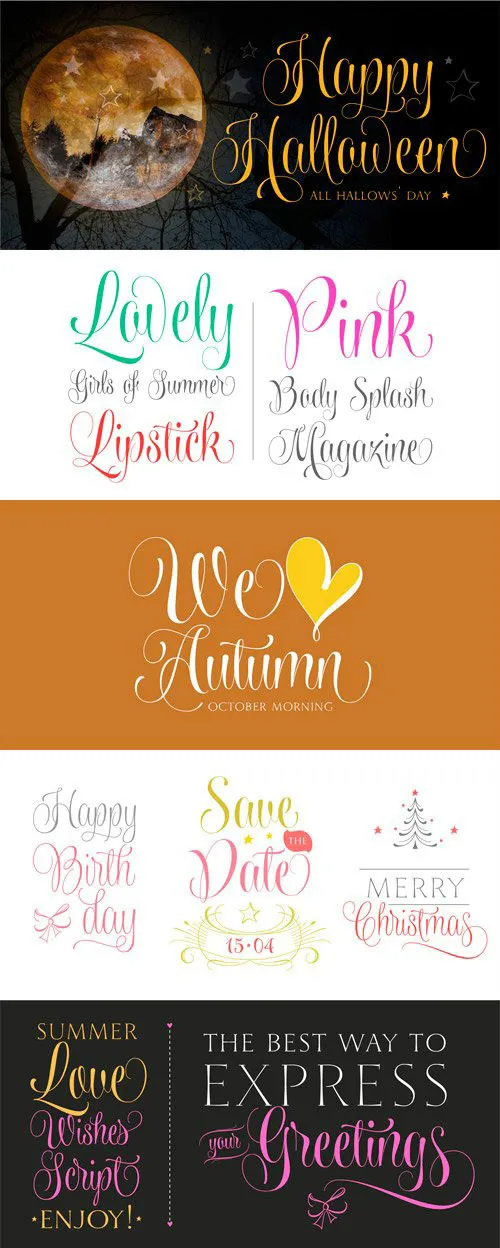
Wishes Script Font – Download Grátis
A Wishes Script Font é uma elegante escolha para designers que buscam adicionar um toque romântico a seus trabalhos digitais. Com traços fluidos e curvados, essa fonte script se destaca com um charme único que combina elementos femininos suaves com sutileza em cada letra. Perfeita tanto para gráficos de casamento quanto para criações de arte, ela representa uma maneira criativa e encantadora de incorporar detalhes personalizados em projetos. Inspirada pela designer Hamilton, essa fonte traz uma atmosfera de serenidade ao trabalho onde você a utilizar, permitindo que sua mensagem ou design seja percebida como um gesto de amor pelo trabalho. Sua versatilidade faz dela uma excelente opção para trabalhos relacionados a cartas personalizadas, arte digital e até mesmo elementos gráficos em anúncios de casamento.